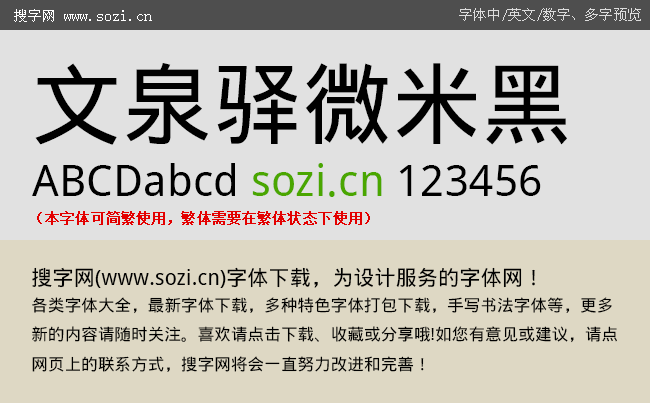
文泉驛微米黑
搜字網(wǎng)給大家提供一款黑體類中文字體文泉驛微米黑字體下載。文泉驛微米黑是一款應(yīng)用于藝術(shù)設(shè)計(jì)方面的中文簡(jiǎn)體漢字,又名文泉驛等寬微米黑,該字體偏粗,字形大方得體,可應(yīng)用于印刷包裝、平面設(shè)計(jì)、廣告設(shè)計(jì)、藝術(shù)創(chuàng)作等行業(yè)領(lǐng)域,喜歡的朋友快下載收藏吧。